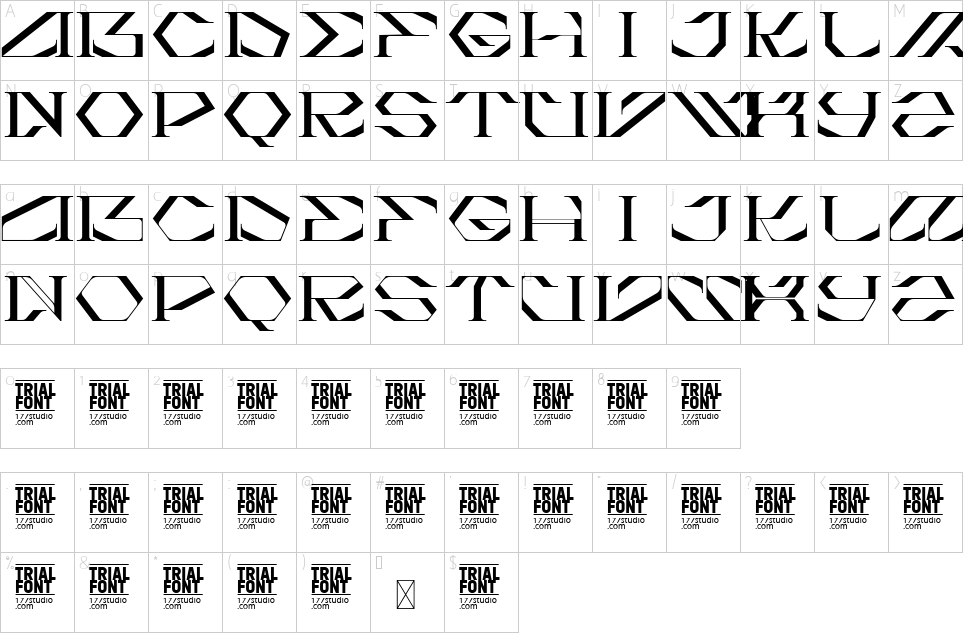
Aqui está uma breve descrição em português para a página de download da fonte ‘Global Maker Font’: Global Maker é uma elegante e versátil fonte que combina facilidade de uso com um conjunto amplo de caracteres, ideal tanto para designers profissionais quanto para iniciantes. Desenvolvida pela 177studio.com, esta fonte foi projetada para atender às necessidades variadas do design digital, oferecendo uma gama de opções que vão desde sinóticos até letras especiais. Com sua simplicidade e facilidade de uso, Global Maker é perfeita para criações digitais. Seja você criando um layout online ou desenvolvendo um projeto gráfico, esta fonte fornece a precisão e qualidade necessárias. Download agora Global Maker Font e faça seu trabalho brilhar ainda mais. Esta fonte é uma opção gratuita perfeita para quem procura qualidade sem comprometer com os custos de design profissional. Com ela, você pode dar vida ao seu projeto, sejam eles websites, aplicativos ou designs digitais.